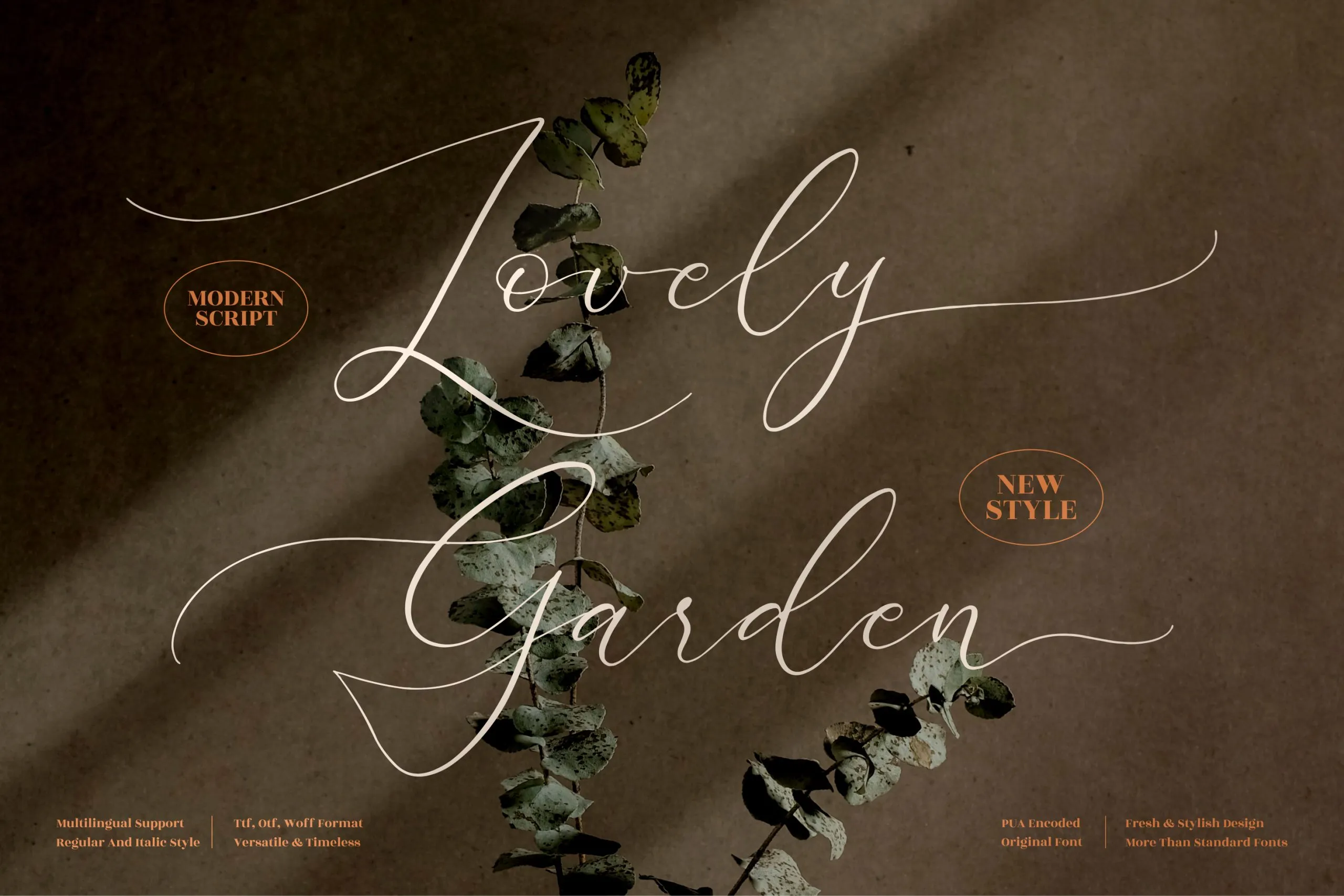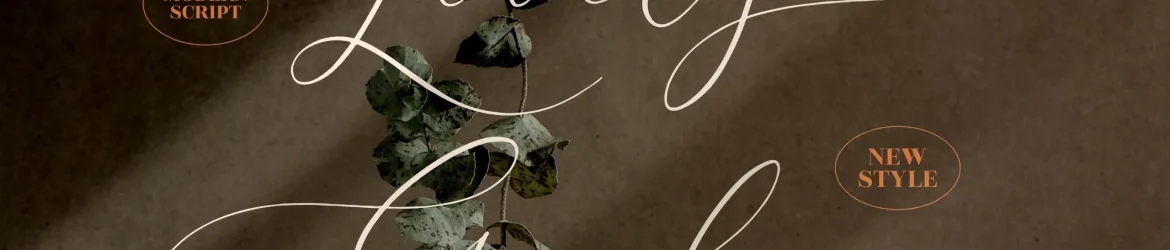
Lovely Garden Font – Download Grátis
Esta é uma fonte de escrita romântica perfeita para projetos variados que necessitem de um sabor delicado e elegante. Afonte ‘Lovely Garden Font’ é ideal para criações como logos, designs de marca, decoração de casa, embalagens de produtos, taças, citações, cartazes, sacolas de compras, roupas personalizadas, capas de livros, cartões de nome, convites, cartões de agradecimento, etiquetas e até mesmo para elementos em fotografias ou selos especiais. Seja qual seja o seu projeto que exija um toque delicado e encantador, esta fonte é uma ótima escolha. Ela encaixa-se perfeitamente com qualquer coisa relacionada a decoração de interiores, arte gráfica personalizada ou criações únicas no mundo da moda. Não importa o projeto que você está tentando alcançar, esta fonte ‘Lovely Garden Font’ está aqui para ajudá-lo a trazer vida e delicadeza ao seu design.